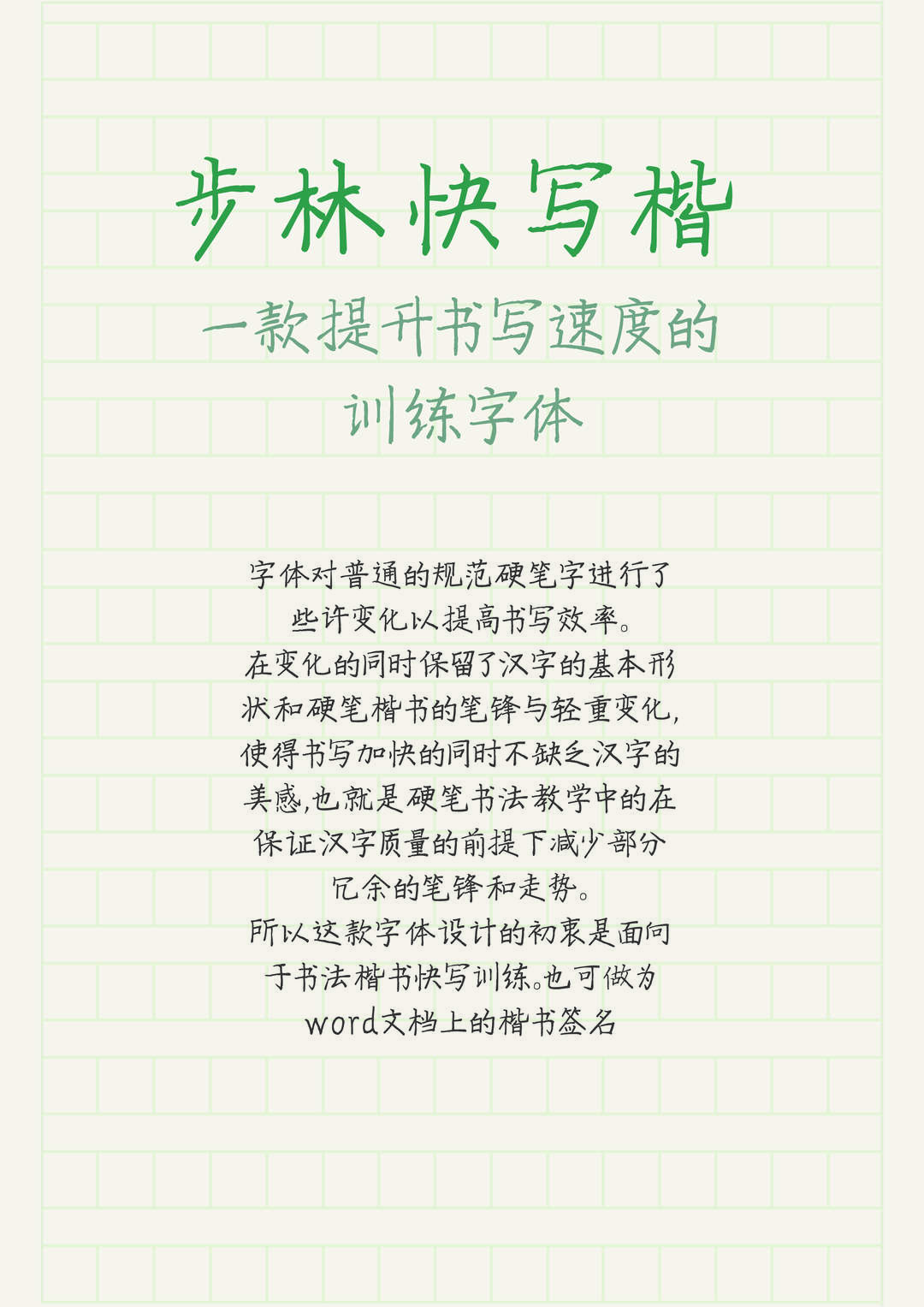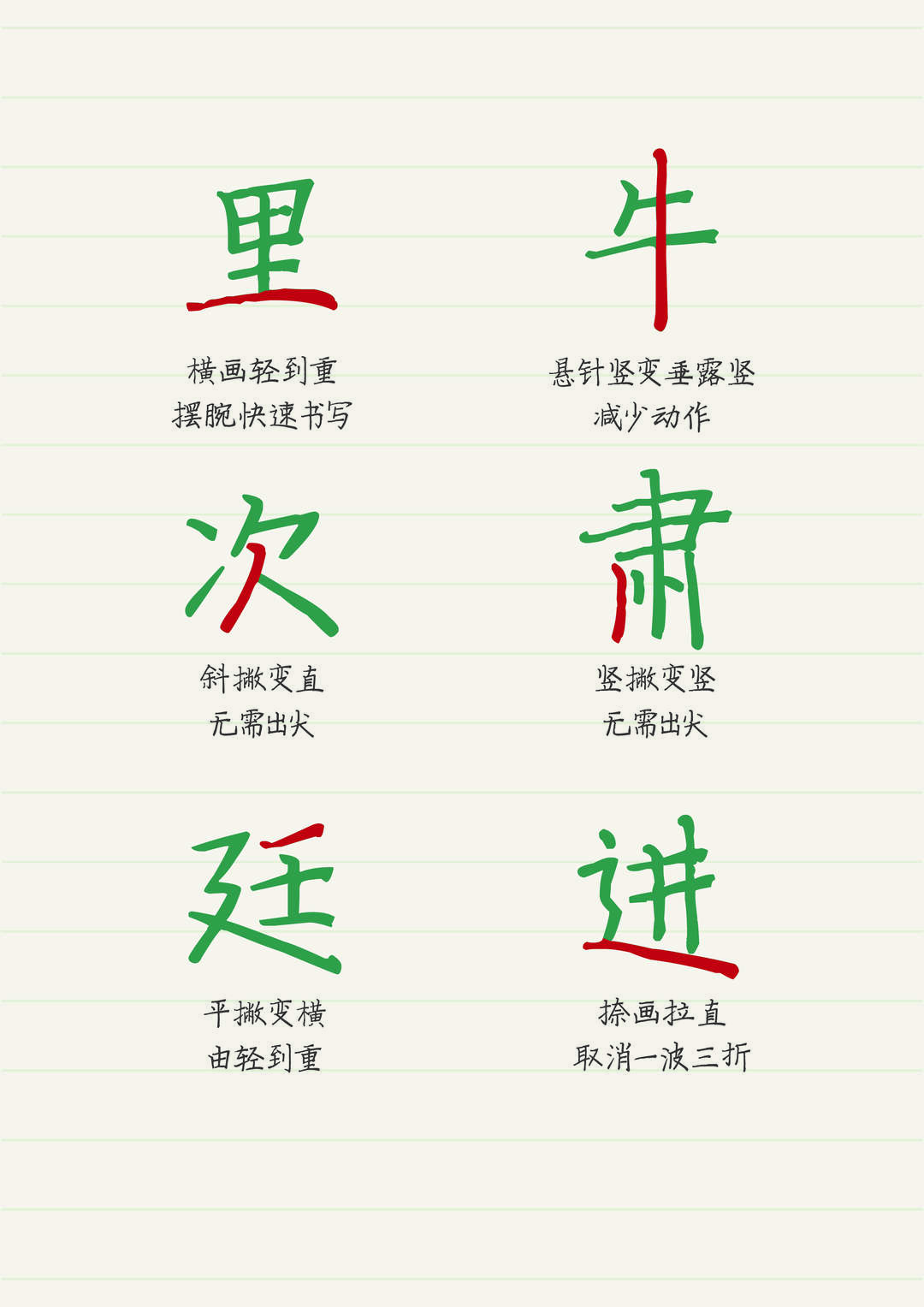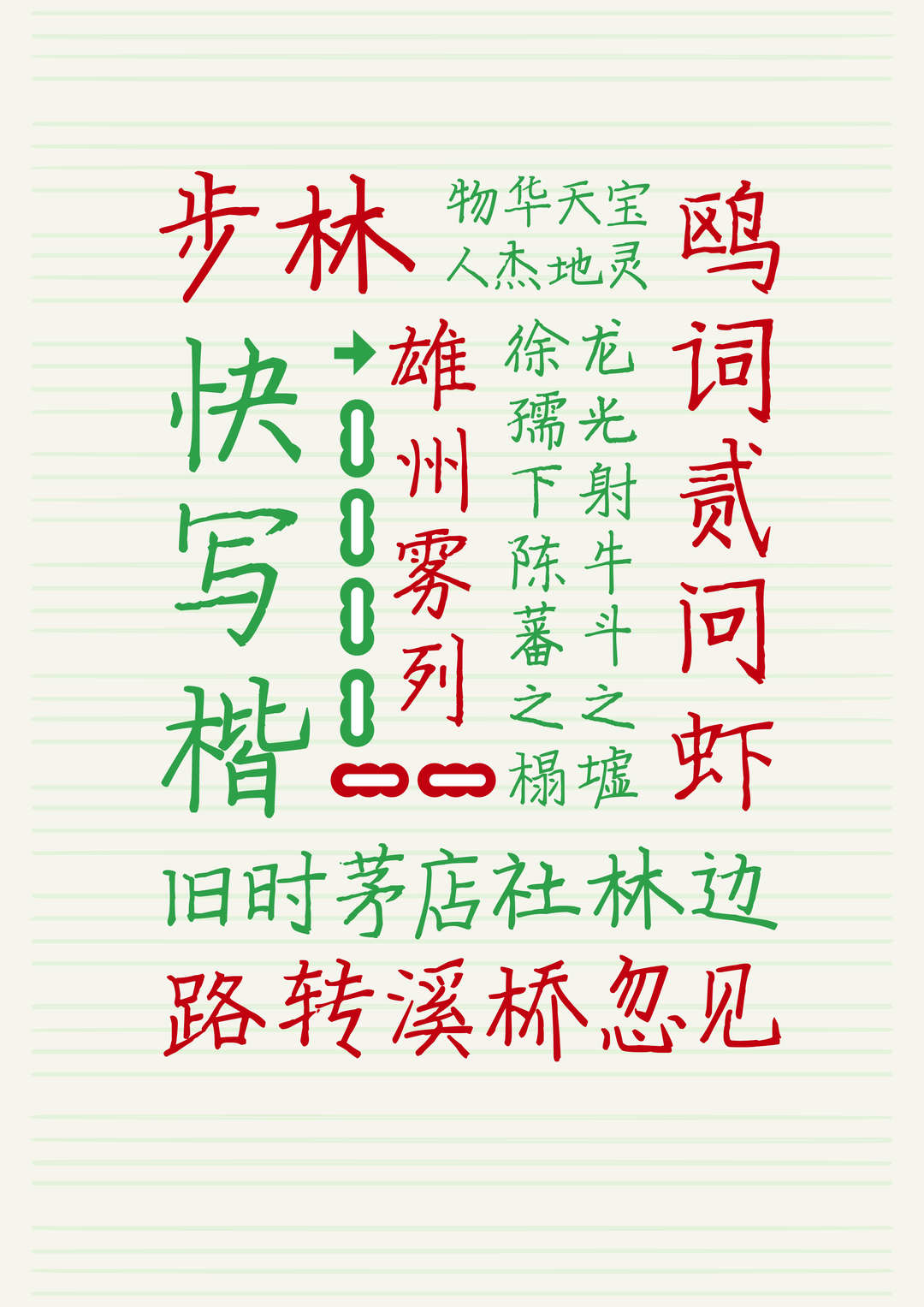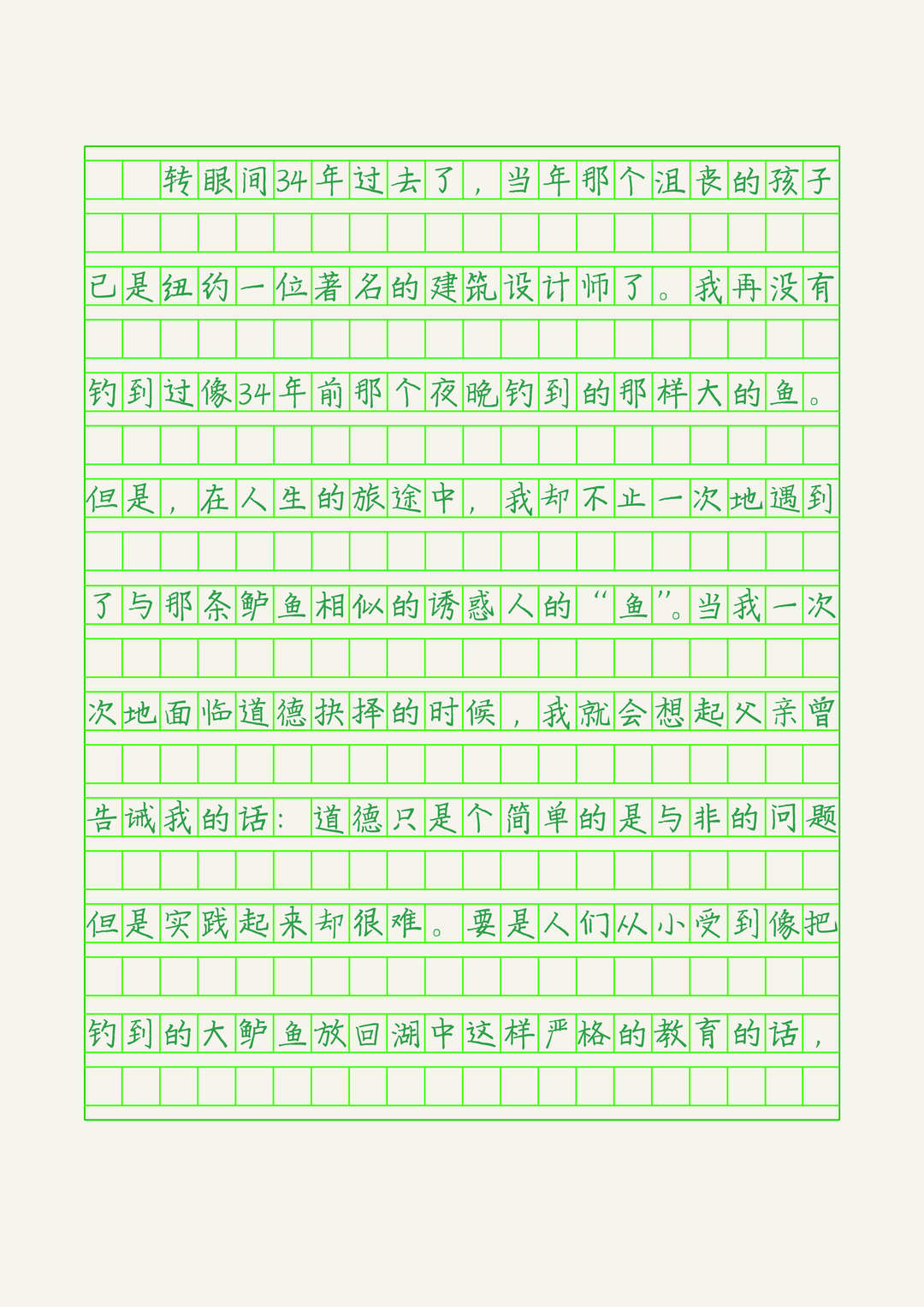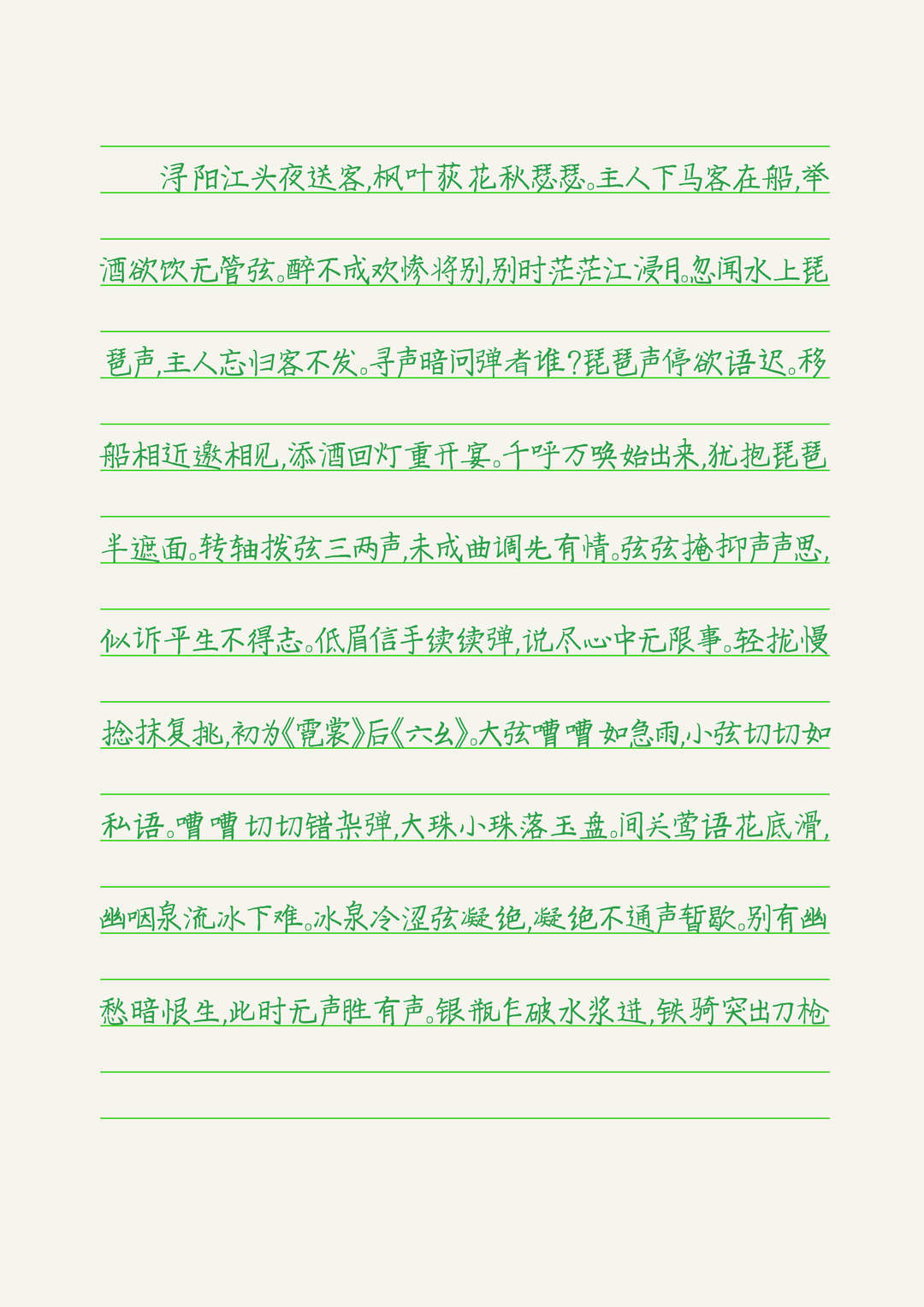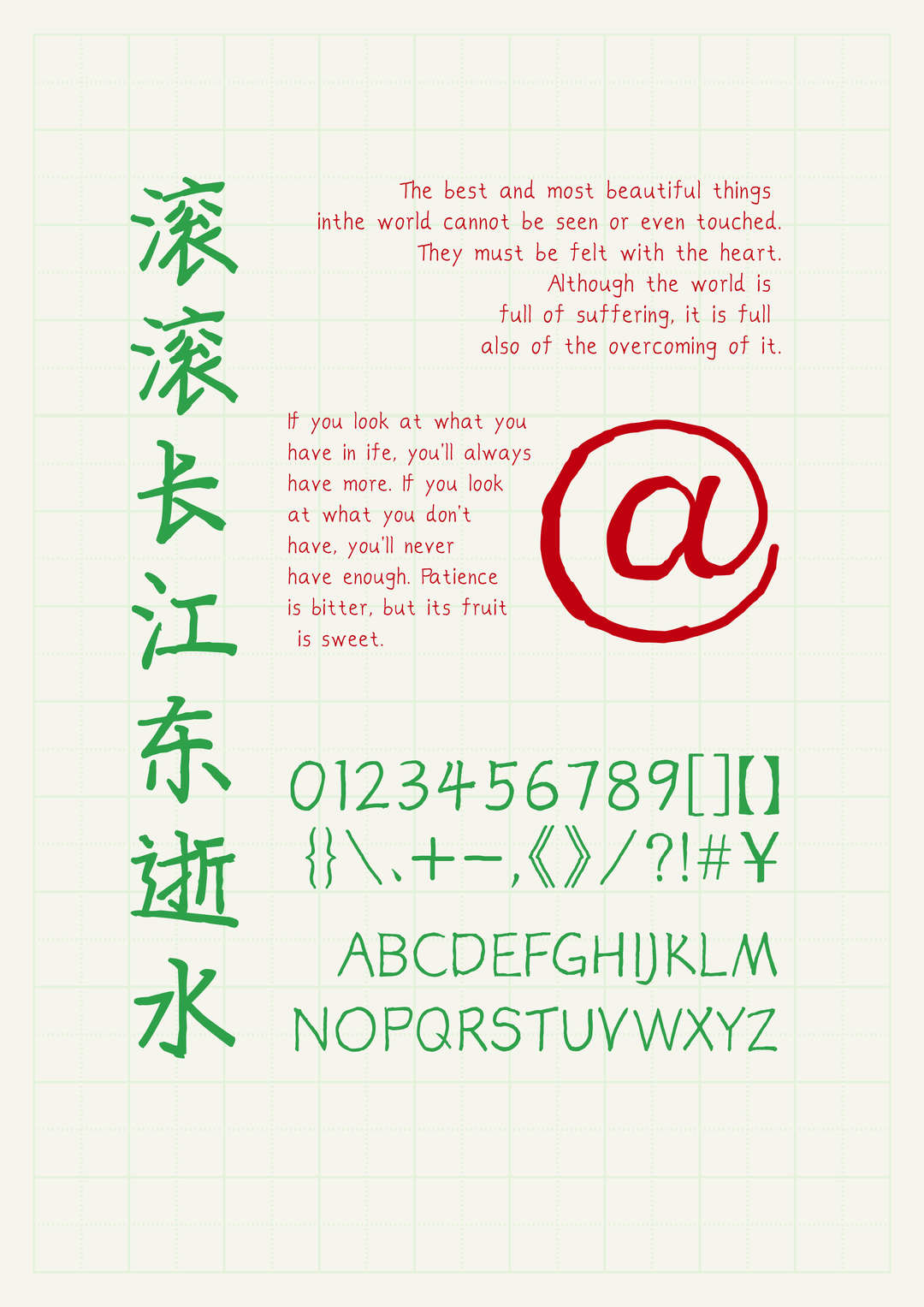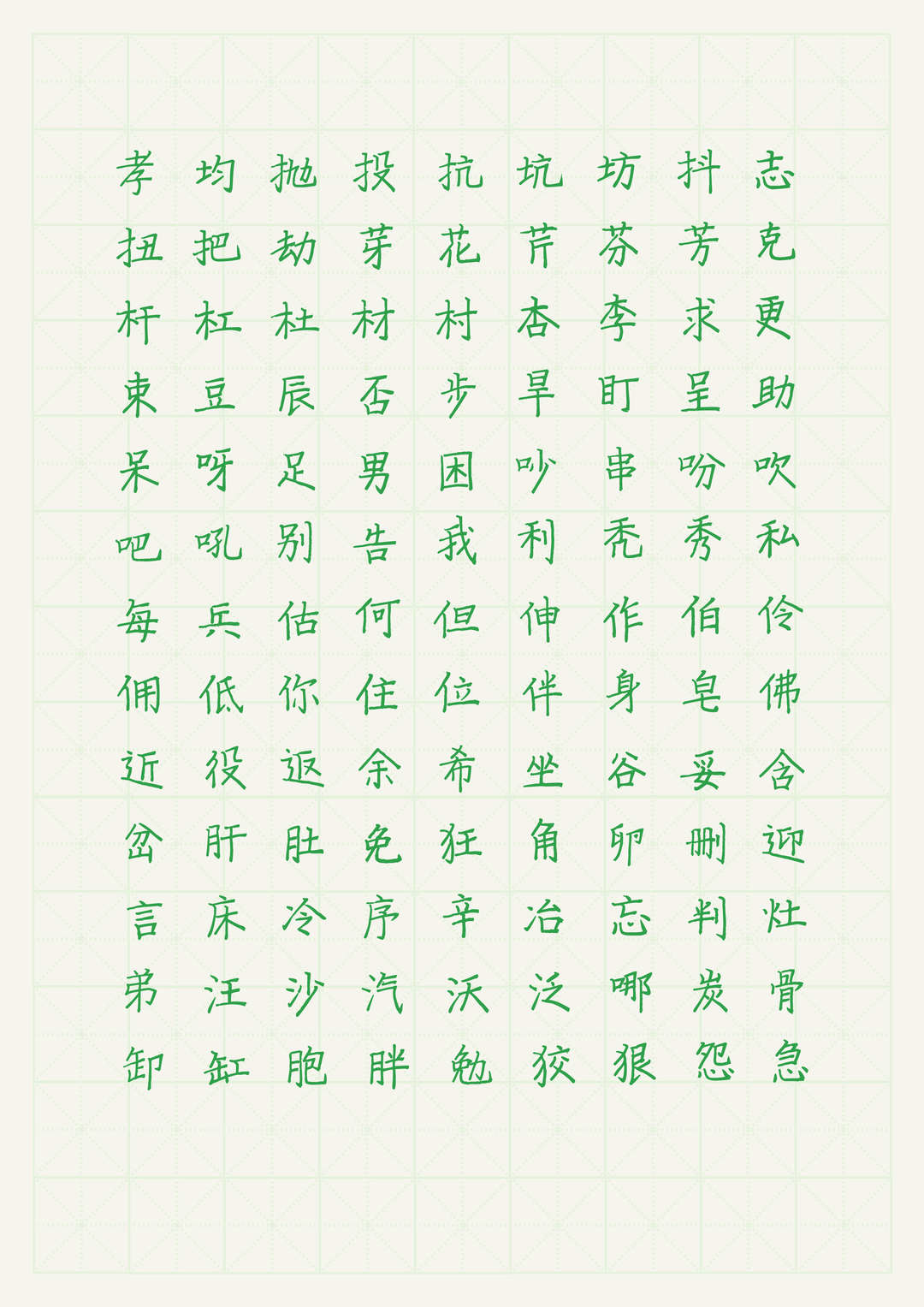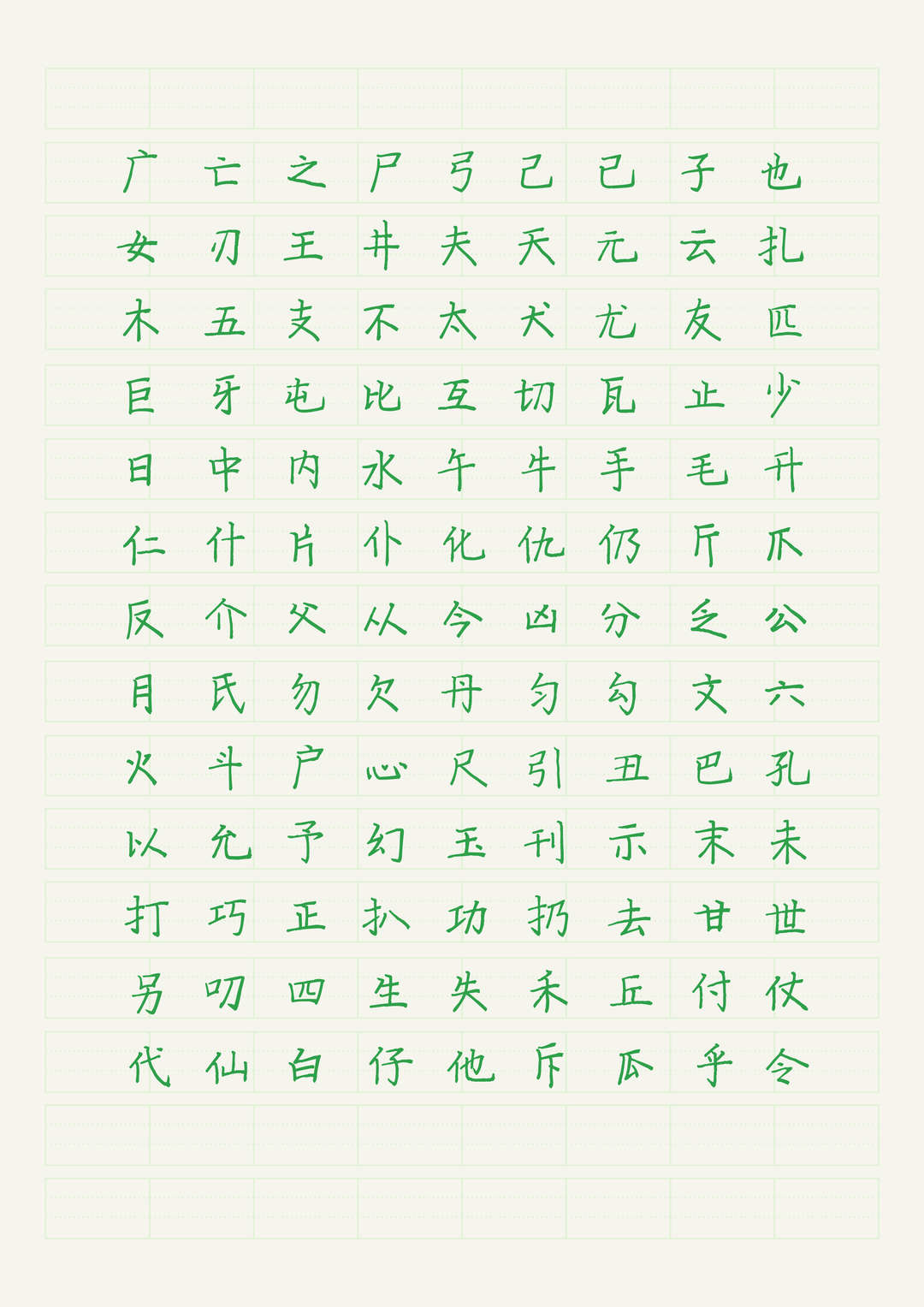
步林快写楷
步林快写楷是一款由字体设计师余思源制作的免费可商用字体。该字体以日常硬笔规范字书写习惯为基础,通过对传统楷书笔画进行适度调整,在保持汉字结构清晰与规范性的同时,减少书写过程中的冗余动作,使文字呈现出更加流畅、快速的书写节奏。
与传统硬笔楷书强调端正、严谨的书写方式不同,步林快写楷更加注重实际书写效率。字体设计过程中,对普通规范硬笔字进行了一些变化,例如调整部分笔画走势、简化部分转折处理,并结合硬笔书写时的轻重变化,让字形更加接近真实书写状态,同时降低连续书写时的负担。
从字形表现来看,步林快写楷保留了楷书稳定的结构特点,横竖撇捺之间具有明确的书写逻辑。字体笔画整体偏纤细,线条带有明显的硬笔书写质感,在保证识别性的基础上,通过减少不必要的停顿和顿笔,让文字呈现出自然、简洁的手写效果。
在部分笔画设计上,字体加入了针对快速书写的优化。例如横画根据书写力度呈现由轻到重的变化,减少刻意停顿;竖画强调连续书写时的稳定感,降低重复起收笔动作;撇捺等斜向笔画则适当调整方向,使整体书写更加顺畅。这些细节使字体既具备练字字体的规范性,又拥有日常记录、笔记书写中的自然感。
从应用场景来看,步林快写楷适合作为硬笔书法练习字体、学生练字参考字体、学习笔记字体以及手账、文案排版等设计用途。相比传统楷书字体,它更加贴近日常书写环境,能够营造出整洁而具有个人笔迹感的视觉效果。
字符方面,步林快写楷支持中文常用字符、英文、数字以及常用符号,可以满足日常文字排版与基础设计需求。字体整体风格清爽自然,既适合用于学习场景,也适合作为需要手写感的视觉设计元素。
总体来看,步林快写楷并不是单纯追求工整效果的传统楷书字体,而是在规范楷书结构的基础上,对笔画走势和书写动作进行了适当简化,更强调书写速度、自然感与字形美观之间的平衡。字体保留了硬笔楷书清晰易读的特点,同时加入较明显的手写痕迹,适合练字、学习笔记、手账以及日常文字设计等场景。对于喜欢楷书字形,又希望文字带有一定快速书写感的用户来说,这是一款具有较强实用性的免费商用字体。